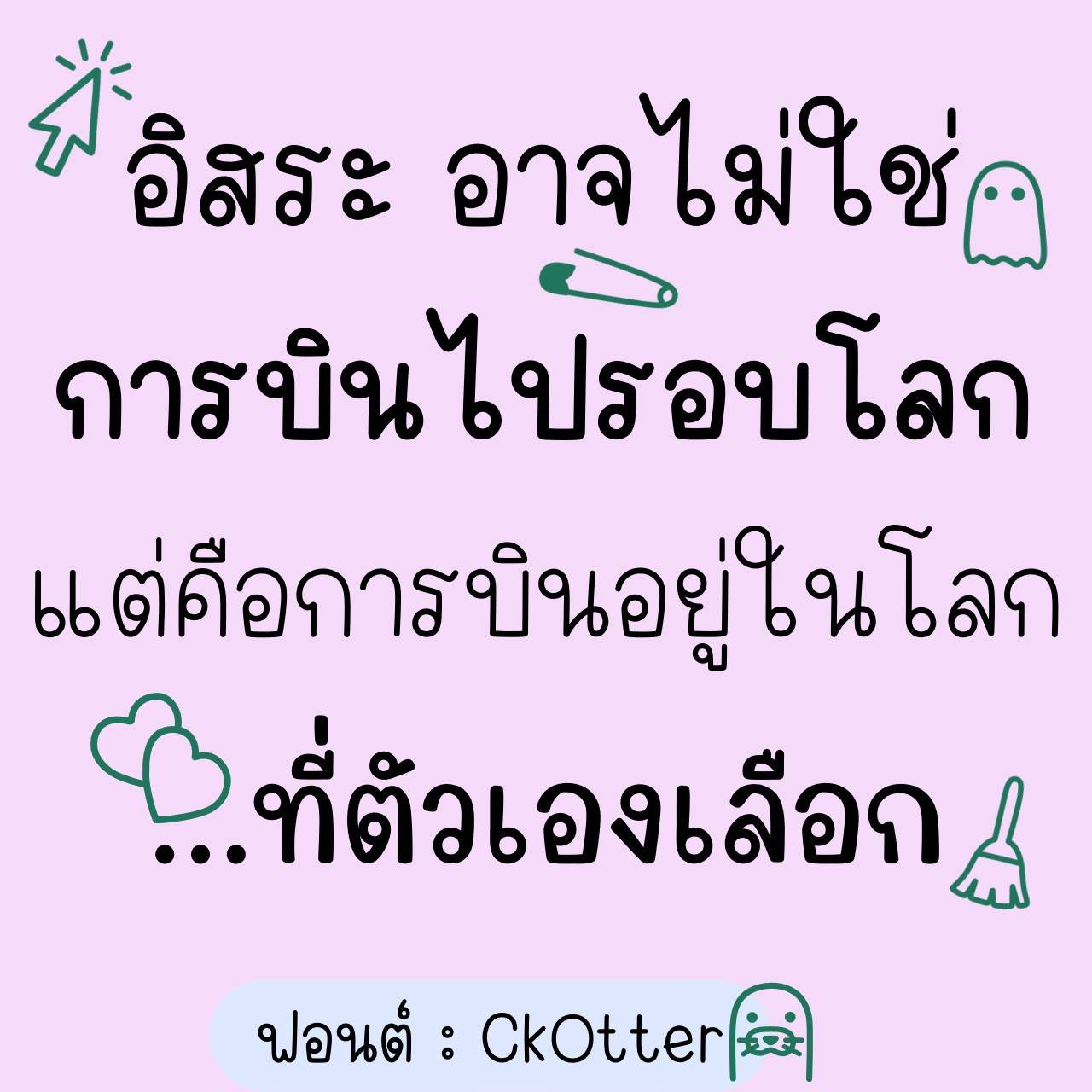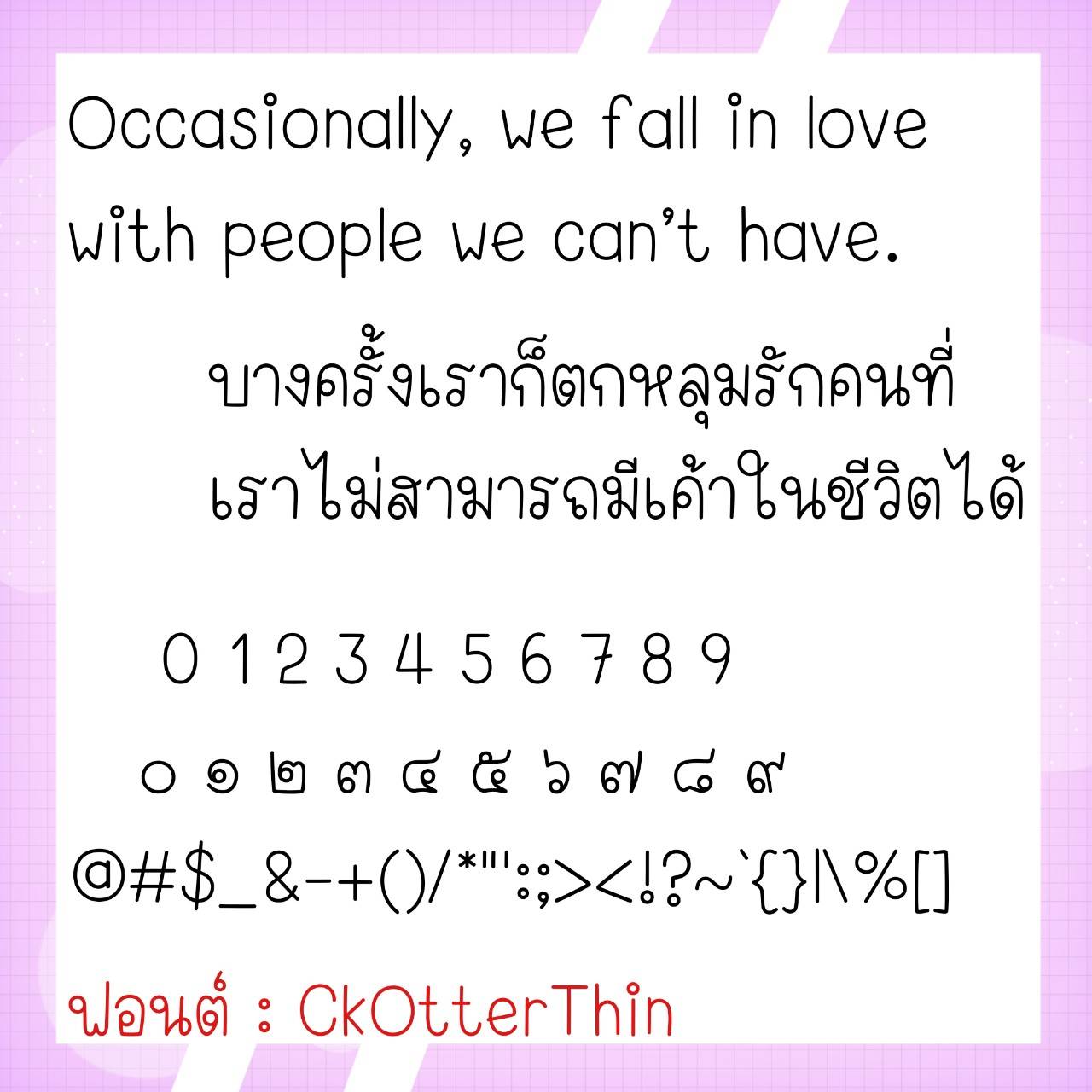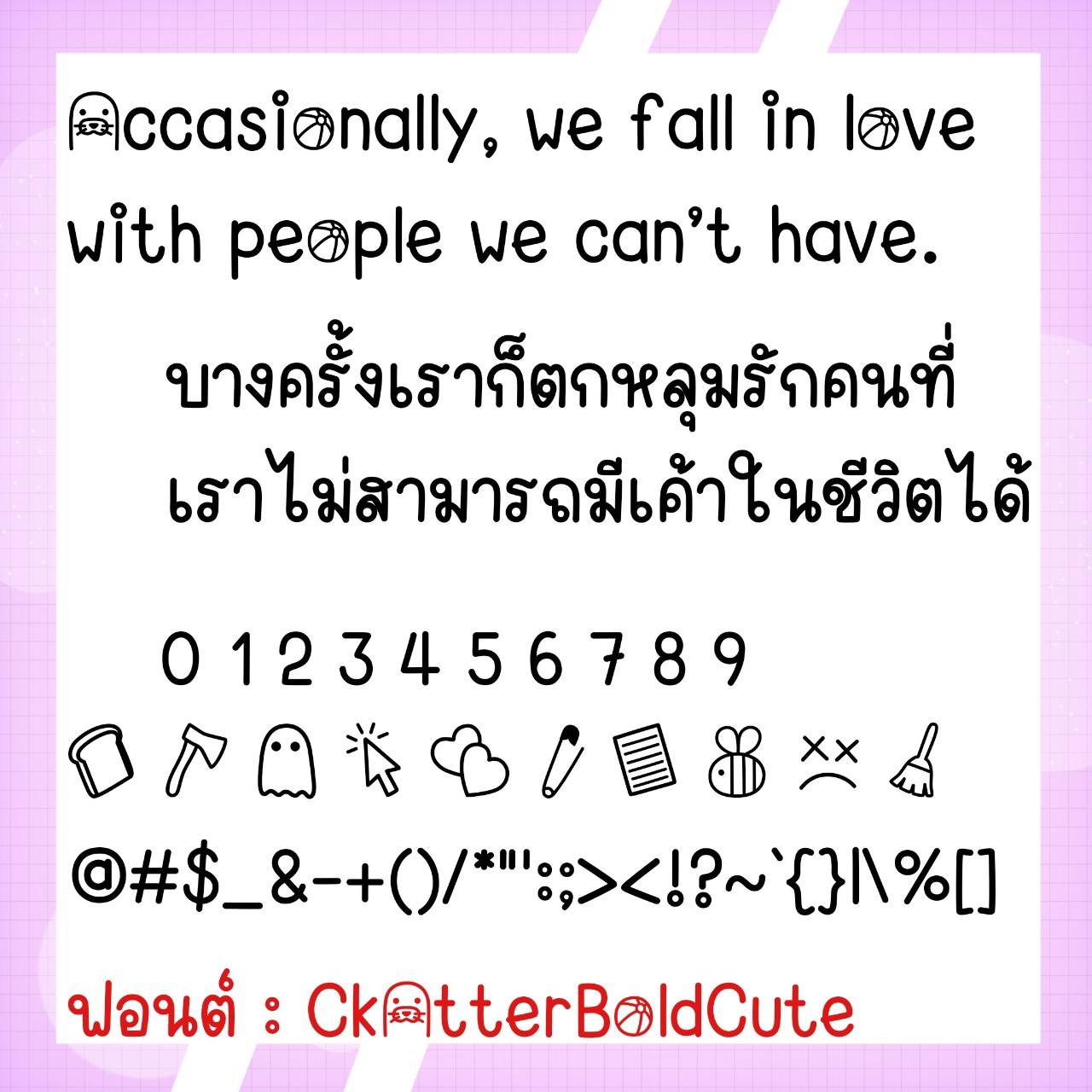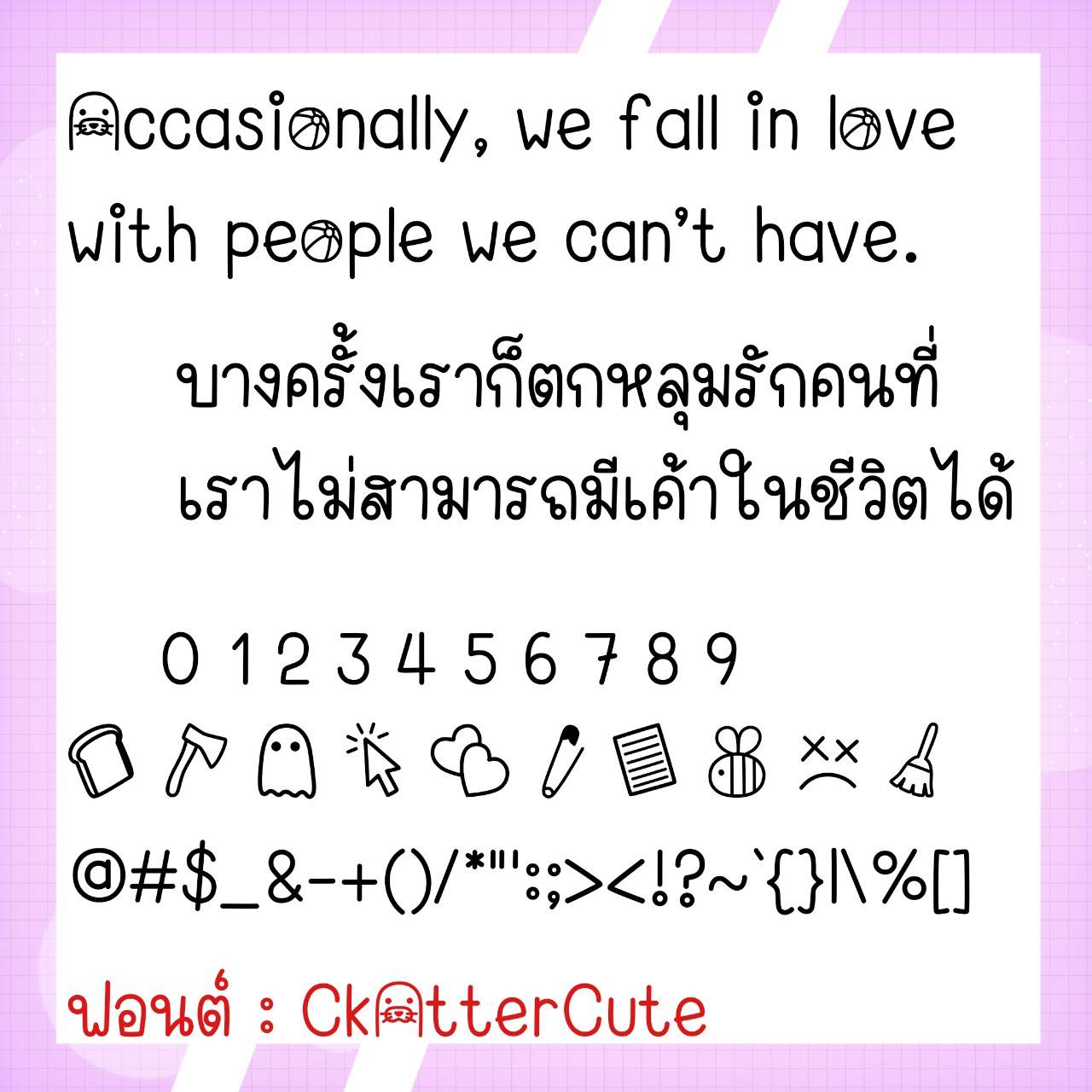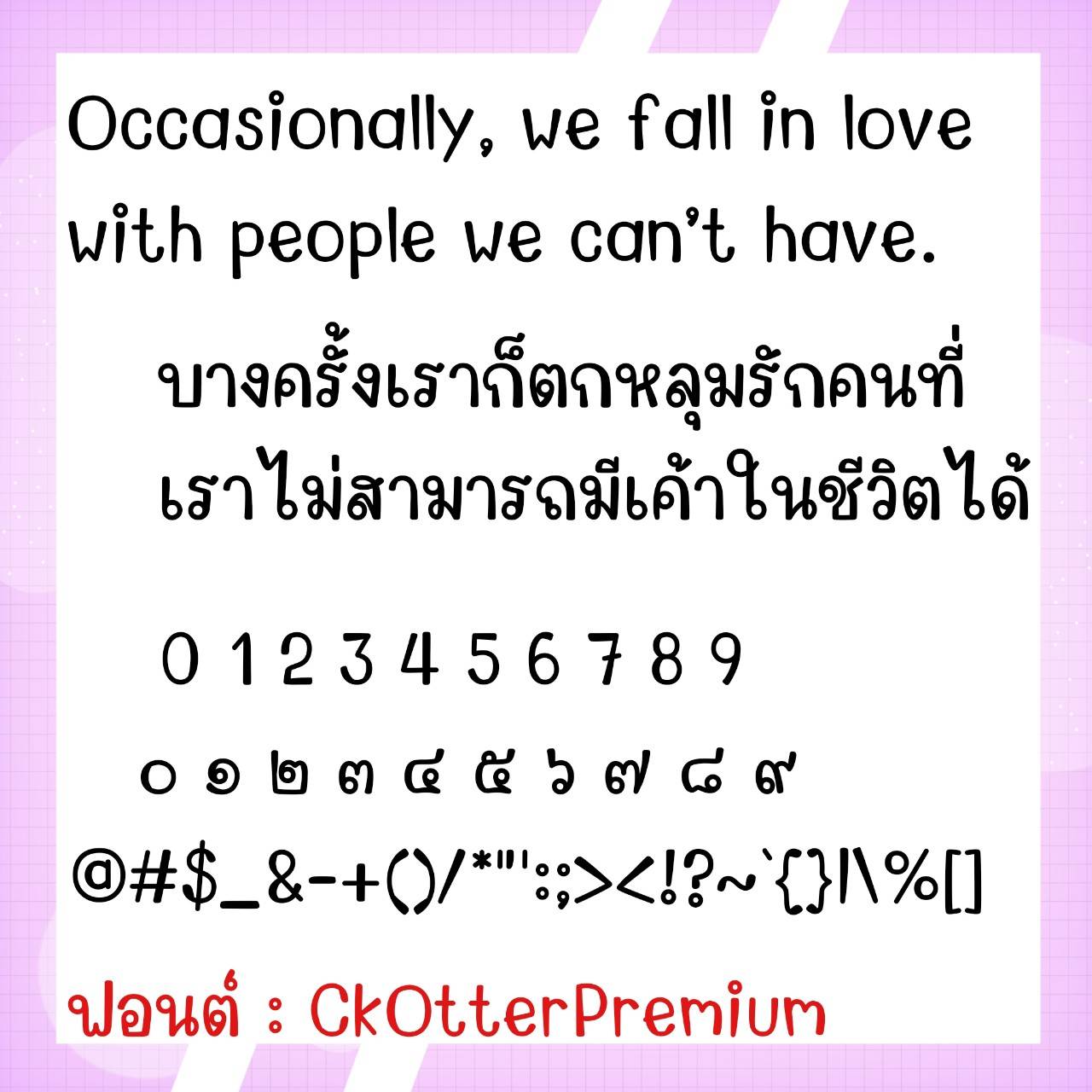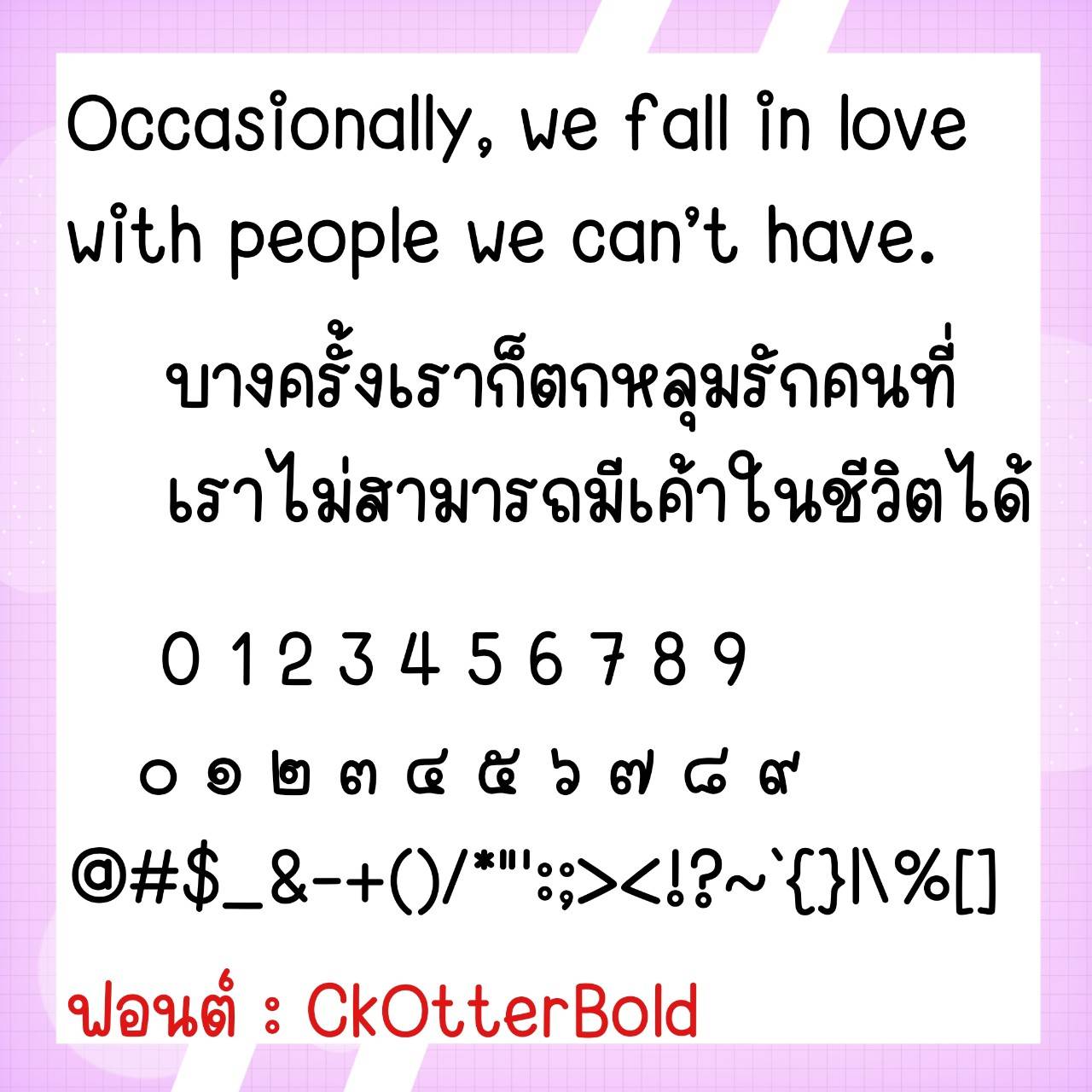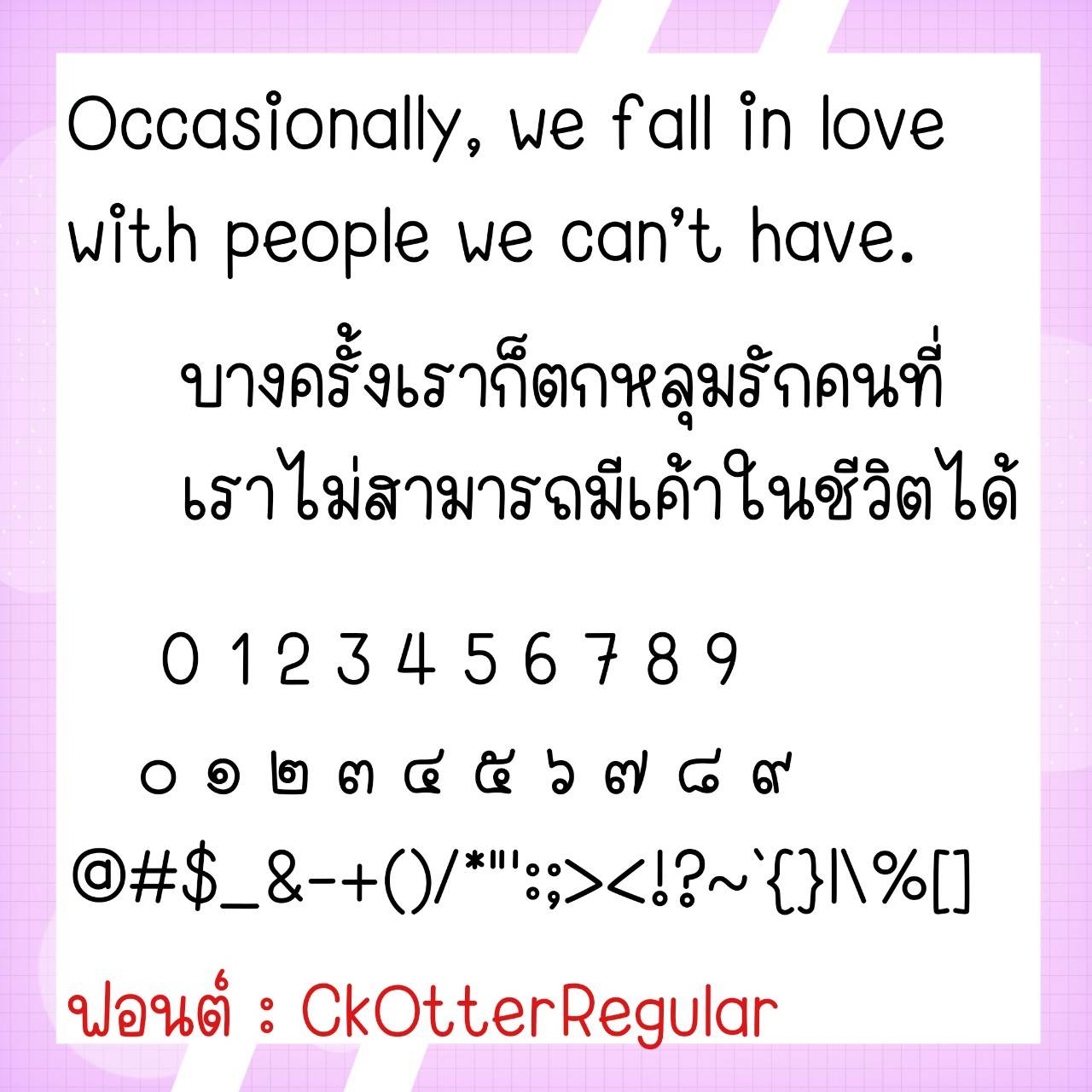
Font CkOtter
ชื่อสินค้า : Font CkOtter 💙
🔸 ฟอนต์ลายมือแนววัยรุ่น หัวกลมน่ารัก ตัวอวบนิดๆ ใช้งานอ่านง่าย เห็นชัดดีต่อสายตาแน่นอนค่ะ และยังมีไฟล์อิโมจิน่ารักๆ ที่ใช้แทนเลขไทยให้ด้วยค่ะ 🥰💙
🔹 A handwritten font for teenagers, cute round head, slightly chubby body, easy to use, clear and good for the eyes. And there is also a cute emoji file that can be used instead of Thai numbers. 🥰💙